Cette année (2025), la fête des mères sera le dimanche 25 mai. Voici de quoi t’inspirer avec de jolis lettering printaniers ! Personnellement, je reste assez classique avec des visuels doux, des effets aquarelle au feutre, des fleurs… Parfois, j’aime jouer la carte du côté moderne et graphique avec un côté plus sobre.
Carte format carte postale 10×15 pour la fête des mères
Ici, on joue avec le côté graphique des mélanges de styles : brushlettering, capitales d’imprimerie avec serif, touches de rose fluo, ombrage gris. Simple et efficace ! A décliner dans différentes couleurs selon l’humeur ! Cela sera toujours pep’s ! Pas besoin de savoir dessiner ! Ce qui change tout, c’est le mélange de typographies.
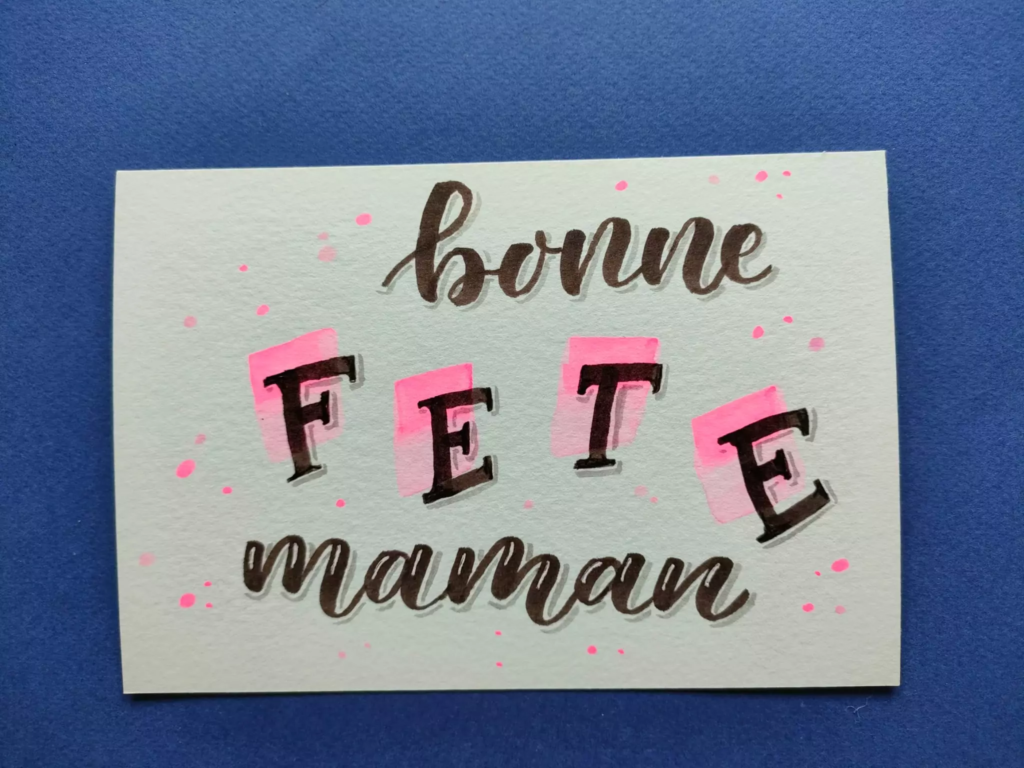
Lettering fête des mère sur iPad (j’ai testé un tutoriel de Teela « every-tuesday »)
Les tons roses et les fleurs, c’est toujours un bon match ! Pas besoin de dessiner des fleurs trop détaillées et réalistes, on joue surtout sur le mix de tailles pour garder un effet assez léger. En revanche, il est intéressant d’entremêler les motifs avec les lettres. un peu d’arabesques pour le côté féminin et élégant ! Sur la chaîne Youtube de l’artiste Teela, tu trouveras beaucoup d’inspiration à l’iPad.
Carte au format carré
J’aime beaucoup le format carré qui peut jouer sur la symétrie ou l’asymétrie selon les envies ! Et aussi, cela me rappelle l’ancien format instagram (ah, nostalgie !)
Ici, j’ai plutôt opté pour du ton sur ton entre rouge et rosé. Impossible de se tromper dans l’harmonie des couleurs ! Les feutres Ecoline permettent de jolies dégradés et des effets aquarelle. Mais c’est possible aussi avec d’autres marques : Faber-castell (mes chouchous, les GoldFaber Aqua ) ou Karin Markers ! Au choix, tu peux directement mélanger sur le papier aquarelle (comme ici) ou utiliser une palette à côté pour des tons plus transparents. J’ai fait un rappel de couleurs en bordure car sinon, je trouvais que la carte n’était pas assez « finie ». Et pour le lettrage, un feutre noir fin fait le travail !
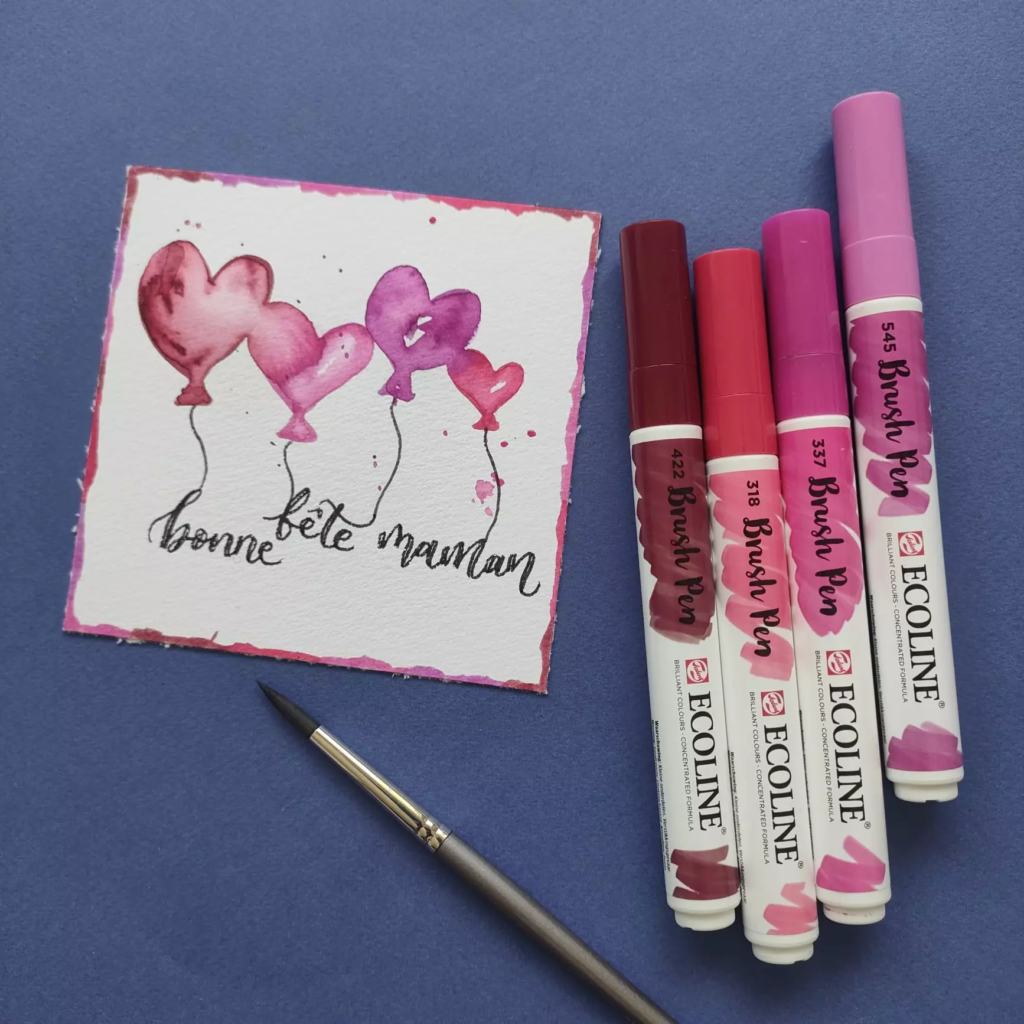
Marque-page pour une maman qui aime la lecture
Le format long peut paraître un défi pour la composition. Mais il ouvre des tas de possibilités créatives et les mamans fan de lecture apprécieront. C’est plus joli qu’un papier qui traîne par là ! Personnellement, j’ai souvent plusieurs livres en cours de lecture (par exemple un roman, un livre business ou un essai) donc j’ai plusieurs marque-pages sur ma table de chevet ou dans ma bibliothèque !!! Une carte de fête des mères utile !
Encore des effets aquarelle ici ! Il faut croire que cela me plaît pour fêter ma maman !!! C’est elle qui m’a donné le goût de la lecture, elle travaillait dans l’édition ! Tu peux imaginer les bibliothèques remplies chez nous ! Du sol au plafond !!! Un vrai bonheur !
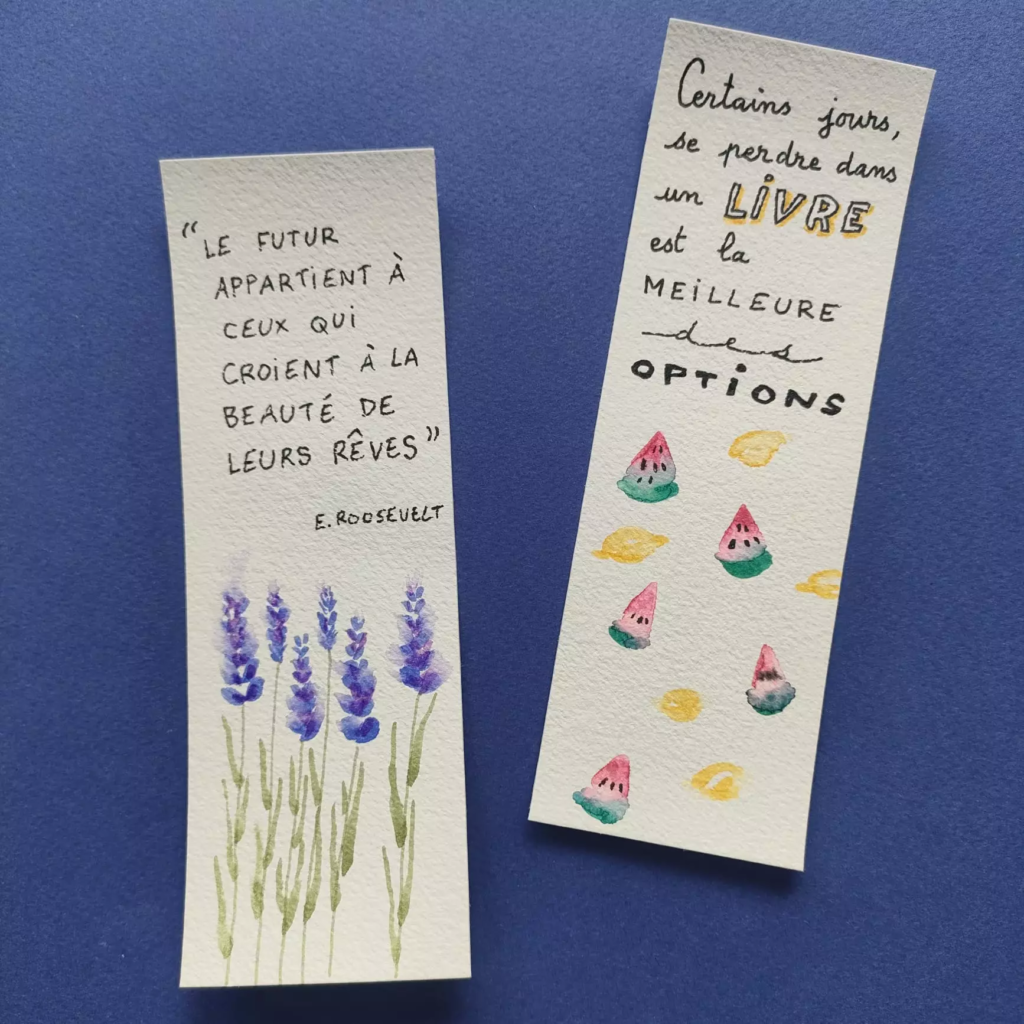
Carte pour accompagner un cadeau de fête des mères
Une étiquette toute simple effectuée avec un seul feutre, un brushpen Faber-Castell. La simplicité a du bon. Mais ce n’est pas si facile de maîtriser le bounce lettering ! Tu connais cette technique ? Elle consiste à ne pas écrire sur une ligne droite. Cela donne plus de dynamisme au lettrage.
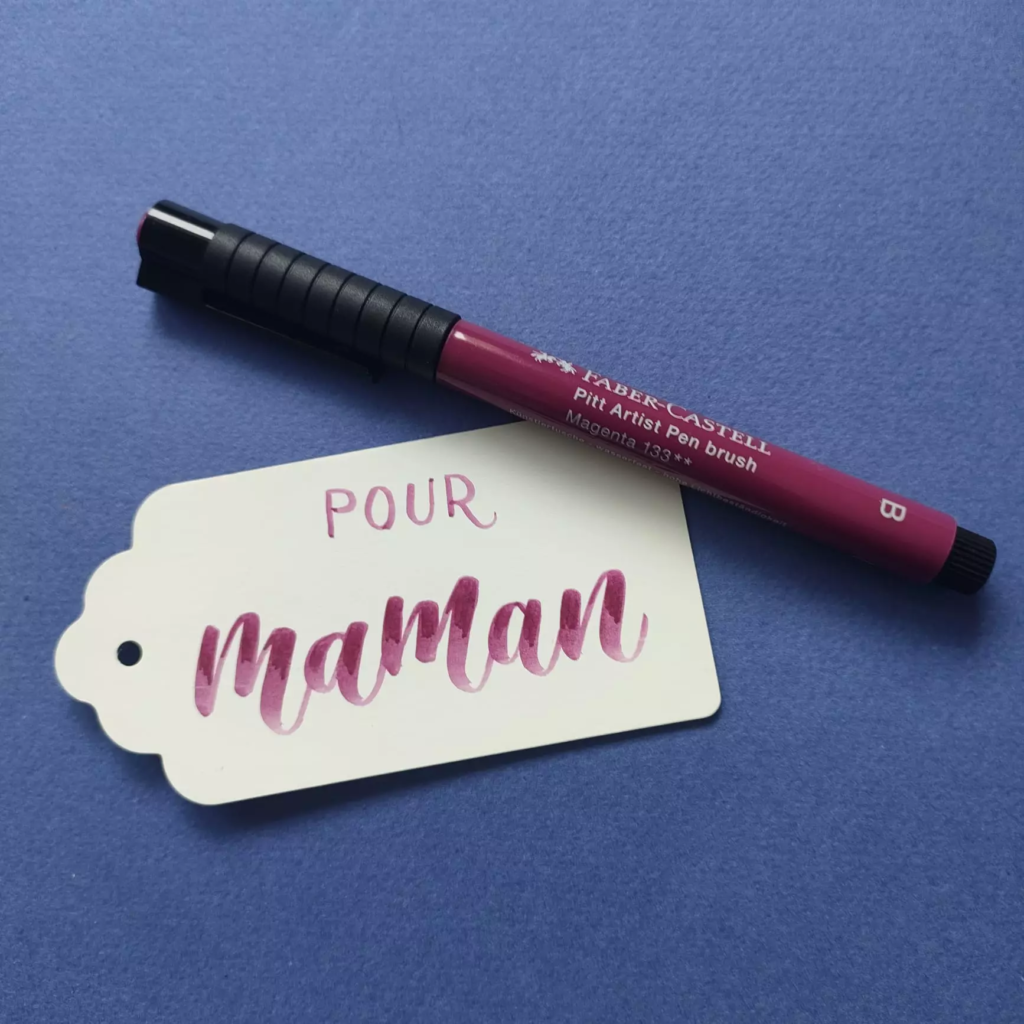
Bonne fête maman avec arabesques (article détaillant la technique des arabesques ici)
J’espère que ces idées de cartes de fête des mères t’inspireront. Je sais que cela fait toujours plaisir en tout cas d’en recevoir faites à la main ! On a tendance à perdre un peu cette habitude, c’est dommage !